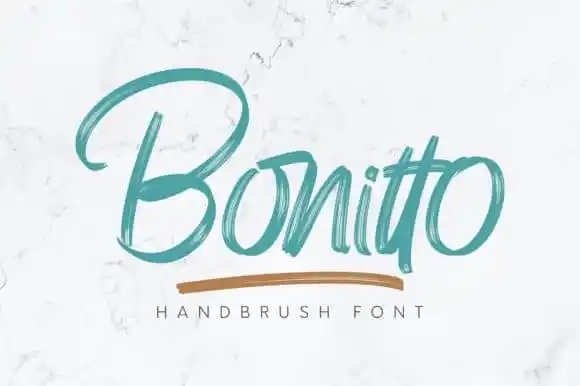
Bonitto Brush Font – Fonte Grátis
Bonitto Brush Font
Bonitto Brush Font é uma escolha única para adicionar um toque especial a seus materiais digitais. Esta tipografia foi projetada por Omotu e oferece uma versatilidade impressionante, adequada para diversos usos média. Com seu design cuidadosamente criado com ajuda de uma caneta brush vibrante, Bonitto é uma escolha perfeita para aqueles que desejam dar um toque único aos seus materiais digitais. Você pode adorar sua diversidade e utilizar-na para criar cartões de boas-vindas apaixonantes, arte de papel estilosa, posts sociais atraentes e muito mais! Como designer ou usuário de design gráfico, Bonitto Brush Font é uma fonte indispensável que vai transformar seus projetos digitais.